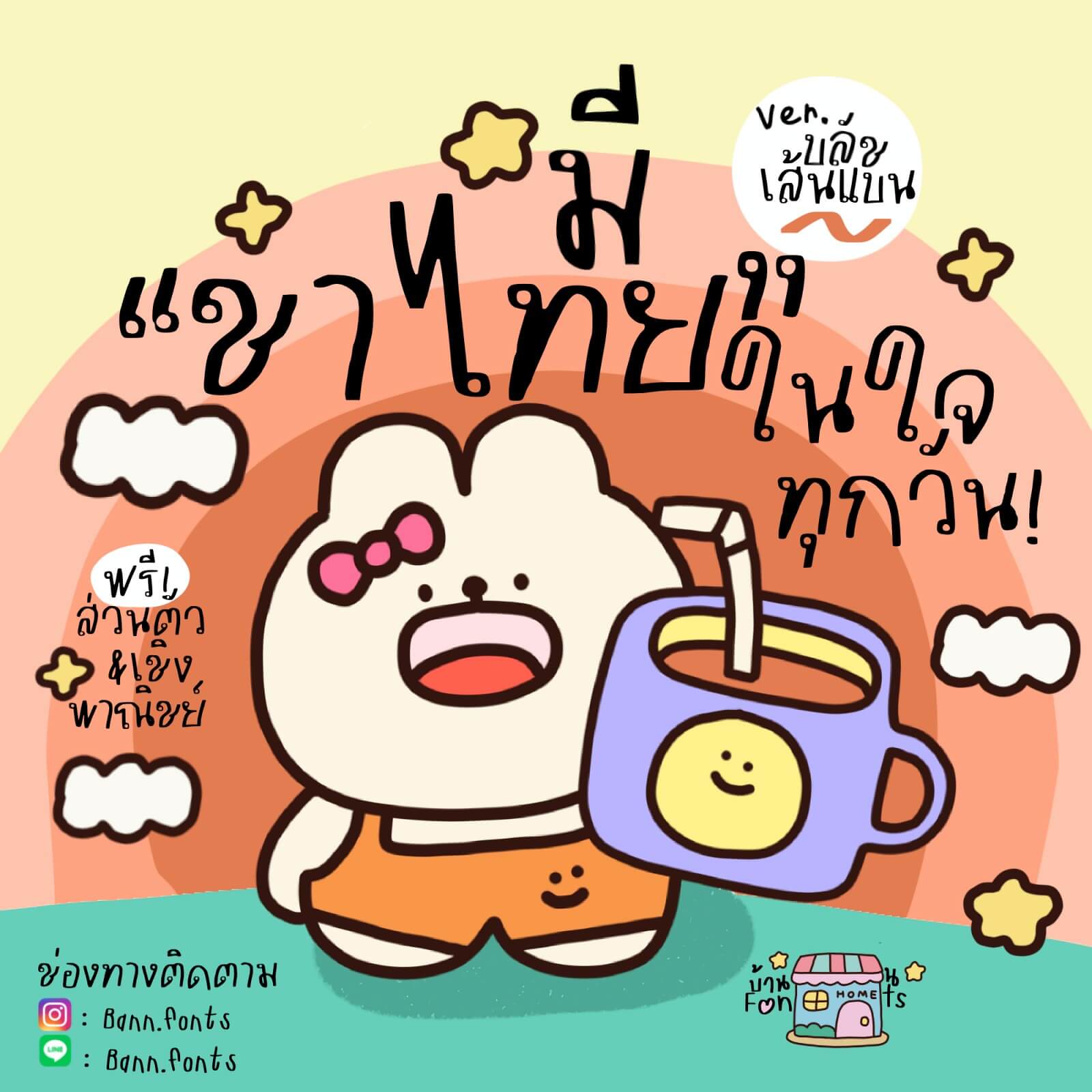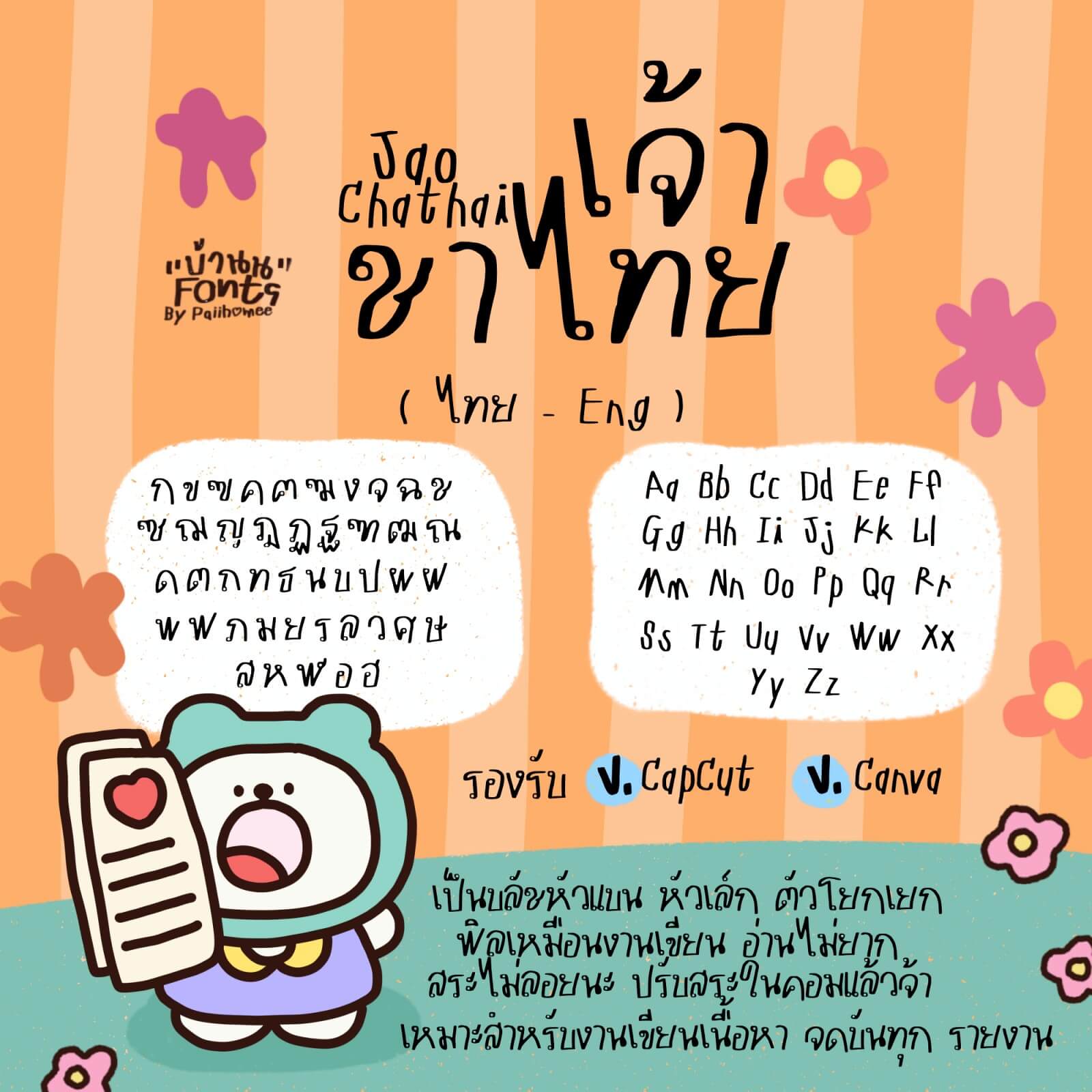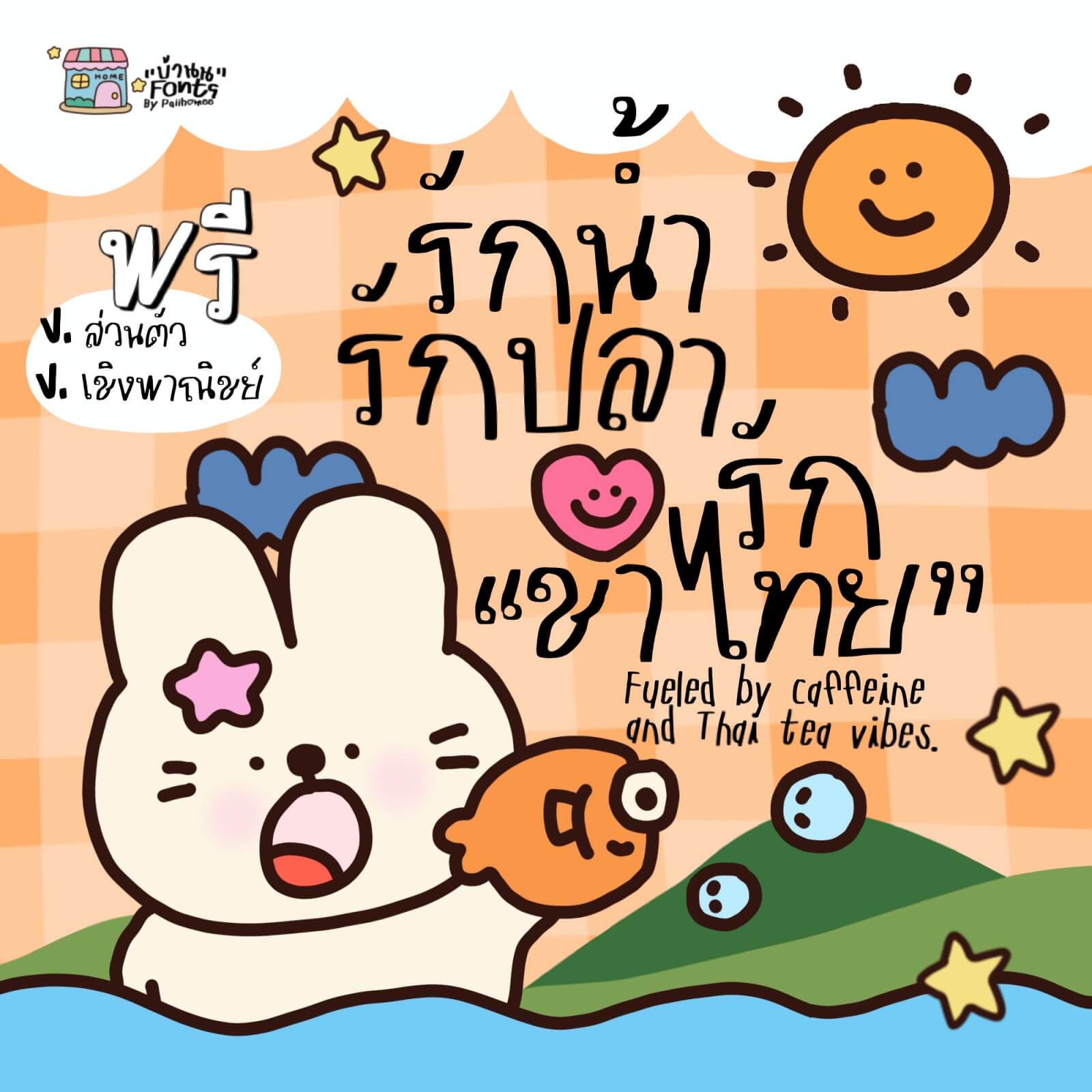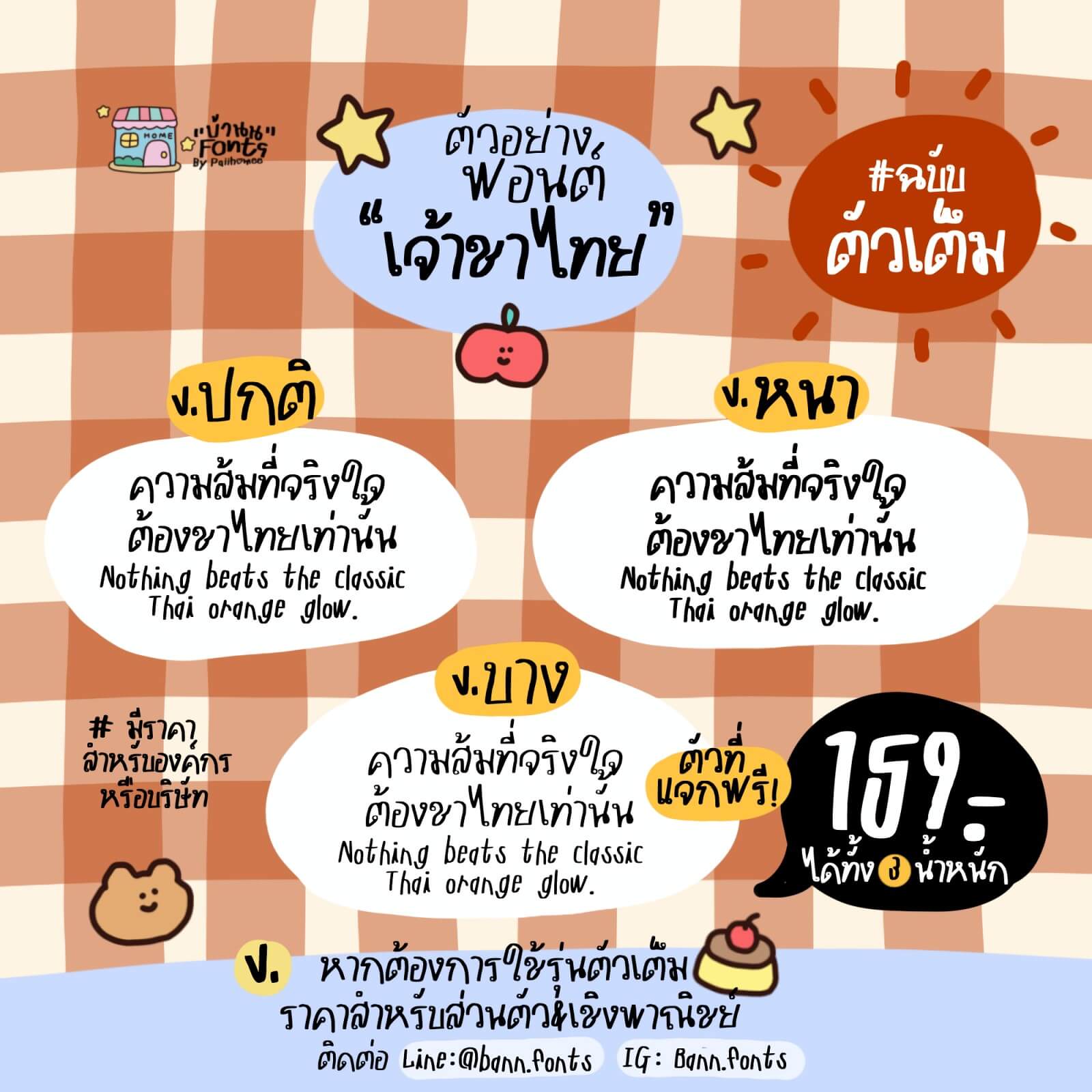
ฟอนต์เจ้าชาไทย – แจกฟรี❗️รุ่นตัวบาง สามารถใช้งานแบบส่วนตัวและเชิงพาณิชย์
แจกให้ใช้งานฟรี สำหรับน้องๆ พี่ๆ ที่ชอบฟอนต์ลายมือตัวโยกเยก มีลูกเล่นน่าสนใจ
แนะนำว่านำไปใช้งานกับการจดเนื้อหา สรุปงาน จดโน้ต จดบันทึก เป็นลายมือโคตรจะเท่เลย หรือจะนำไปทำคลิป แต่งรูป ก็เริ่ดสุดๆ อ่านไม่ยาก ถูกใจวัยรุ่น มีติดเครื่องไว้เลย แนะนำสุดๆ
เจ้าชาไทย (JaoChathai)